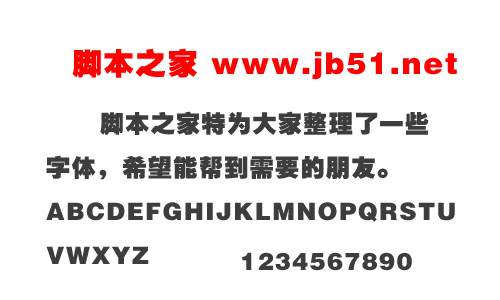
方正超粗黑體簡(jiǎn)體字體是方正字體庫(kù)中的一款超粗中文字體,方正超粗黑體簡(jiǎn)體是方正字體中字體效果比較粗的一款字體。如果嫌字體不夠粗,這款字體絕對(duì)可以滿足你的要求。方正超粗黑是一款創(chuàng)作較早的黑體,字形結(jié)構(gòu)比較傳統(tǒng),中宮緊湊,筆畫(huà)粗重堅(jiān)實(shí)。在傳統(tǒng)的幾款黑體字中,這款字體的筆畫(huà)是最粗的。方正超粗黑的字形風(fēng)格莊重醒目,適用于報(bào)紙、雜志中的大標(biāo)題,以及具有力量感的廣告標(biāo)語(yǔ)。